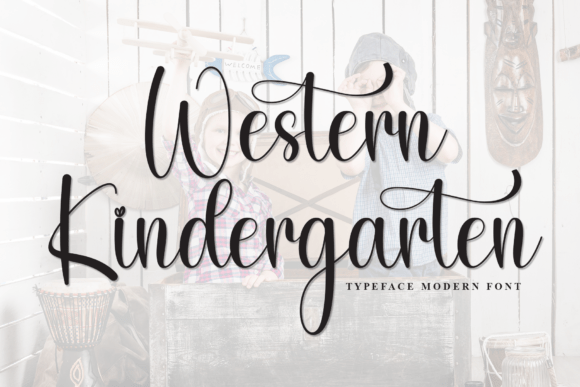
Western Kindergarten
์ •๋ฐ€ํ•˜๊ฒŒ ์ œ์ž‘๋œ Western Kindergarten๋Š” ๊น”๋”ํ•œ ๋ฒกํ„ฐ, ๋ถ€๋“œ๋Ÿฌ์šด ํƒ€์ดํฌ๊ทธ๋ž˜ํ”ผ ๋ฐ ์•ˆ์‹ฌํ•  ์ˆ˜ ์žˆ๋Š” ์ƒ์—…์šฉ ๋ผ์ด์„ ์Šค๋ฅผ ์ œ๊ณตํ•ฉ๋‹ˆ๋‹ค.